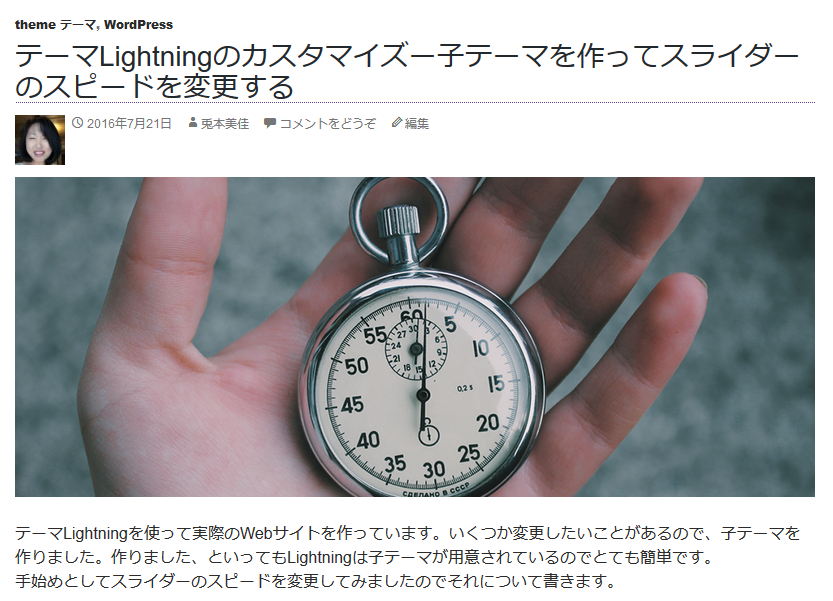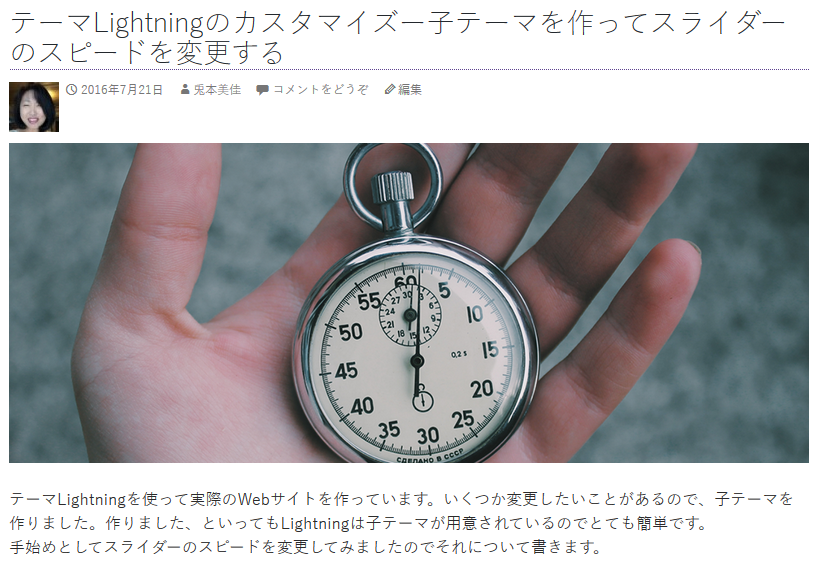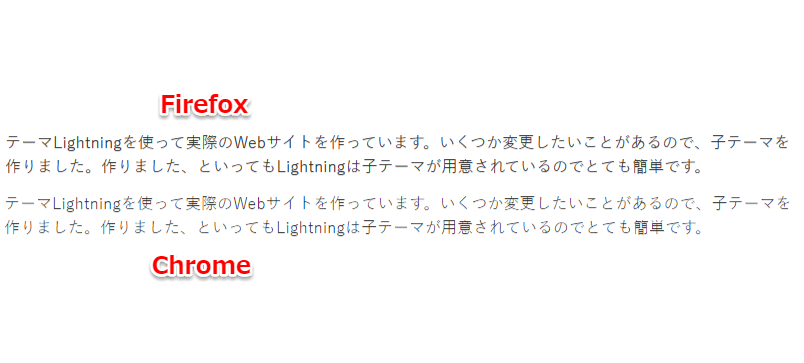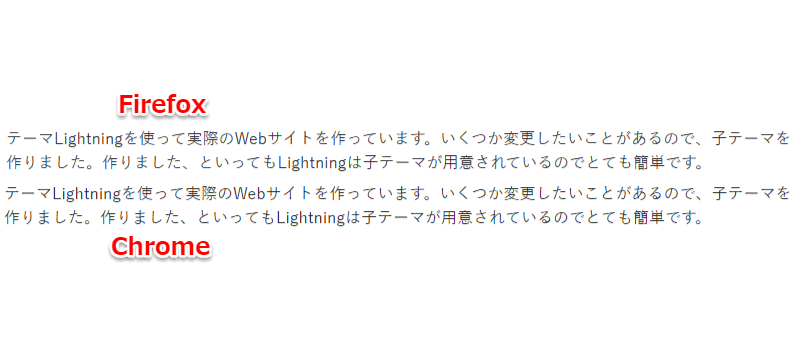
ブログのフォントをWindowsにもMacにもインストールされている游ゴシックに変えてみた
このblogは2年前の3月から書いていますが、当初に設定して以来font-familyを変更していませんでした。当時としてはこれがベスト!と思われる設定でした。
先日、WindowsにもMacにもインストールされている游ゴシックというフォントがあることに気づきましたのでそろそろfont-familyも変えてみようということで変更してみました。
font-familyで指定したフォントは各PCに入っているフォント
今(原稿を書いている)現在、このblogのfont-familyは
で指定したままとなっています。つまり、
です。font-familyで指定したフォントは、このblogをみてくれる人のPCなどが持っているフォントで表示されるためMacなら「ヒラギノ角ゴ ProN W3」で、Windowsなら「メイリオ」で表示されることになります。私がいつも使っているのはWindows10なのでメイリオでblogは表示されています。
WindowsでもMacでも同じフォントで表示したい場合は
で書いたようにWebフォントを使うことで実現できました。この方法ならWindowsでもMacでも同じフォントで表示できますが、設定が面倒だったりフォントが有料だったり、読み込みが遅くなったりします。
游ゴシック とは?
そこで游ゴシックの出番となります。游ゴシックはWindows8.1、MacではOS X Mavericksから標準搭載されました(その他に、游明朝もはいっています)。
それまではWindowsとMacに共通するフォントがなかったためにそれぞれ別のフォントで表示していたWebサイトも比較的新しいPCであれば同じように表示されるということになります。
游ゴシック、游明朝その他2書体をまとめて游書体という書体ということです。
このWikipediaをみると、「字游工房初の独自書体」ということだそうです。字游工房さんのWebサイトを見るとそれまでもかなり実績のあるフォント制作会社さんのようですが、はじめて作った独自書体がMacOSやWindowsに取り入れられるってすごい!なんだか映画になりそうな、気がしました。
font-familyに游ゴシックを追加してみてみる
font-familyに游ゴシックを追加してみます。子テーマのstyle.cssで
となっているfont-familyに
游ゴシックを追加しました。
今までは、
このように表示されていたものが、読み込み直すと
ちょっと線が細く、上品な感じ?のフォントになりました。
chromeだけ、色が薄くなってしまう問題を解決
先ほどのスクリーンショットはFirefoxでみたときのものなのですがChromeでみてみるとなんだかフォントが薄い?感じがします。
わずかですがChrome(とVivaldi)で見たときだけ薄いです(Edge,IEでは感じませんでした)。
これについて検索したところ、
Windowsで游ゴシックが汚いのは、どう考えてもWebデザイナーが悪い?
という記事を見つけました。どうもやっぱりChrome(とVivaldi)だけfont-weightが違う解釈になってしまうようです。
ということで、
文字の太さを指定する font-weight:500; を追加してみました。
再度読み込み直すと、
と、ChromeやVivaldiで見ても文字が薄すぎない状態になおりました。
問題発生!このblogで多用しているstrongが太文字にならない…
と、これで解決した…と思ったところ問題が発生しました。font-weightを指定する前は
このように太文字で表示されていた
Lightningの<strong>子テーマ</strong>は作成元である株式会社ベクトルさんが準備してくれています。
strong指定した文字「子テーマ」が、
なんということでしょう(;;)、太文字にならなくなってしまっています。うーん。
試しにfont-weight指定を外すと元のように太字になるので、どうもこの指定方法だとstrongで太文字にできなくなってしまうようです。。。
いろいろな情報でみなさんfont-weightで修正しているのでもしかするとtwentyfourteenの子テーマでなければ、大丈夫なのかもしれません。あるいはみなさんあまり strong を使われていなくて、この問題は気にならないのかもしれません。
しかし、太文字を多用している(^_^;このblogだと大きな問題になってしまいます。
フォントを游ゴシック Mediumに変更する
さて…と思って色々検索をしてみました。そしてこの記事を見つけました
Windowsの游ゴシックをfont-weightを使わずにMacに合わせる方法
ここに書いてあるようにWindowsをMacに合わせたいということではなかったのですが、試しにこの方法を取り入れてみました。
font-familyに “游ゴシック Medium”, “Yu Gothic Medium” を追加して、font-weightは削除しました。
これで読み直してみたところ、
文字の色も細すぎず(游ゴシック Mediumが指定してあるため)、strongが太字で(font-weightを指定してないため)表示されるようになりました。
まとめ:太字を多用しているWebサイトで游ゴシックを使うときは注意?
まだtwentyfourteenでしか試していないので、確かなことは言えないのですが游ゴシックをfont-familyで使うときは
・ChromeやVivaldiで文字のweightがなぜか低くなり 薄く見える
・かといって全体的にfont-weightを指定するとstrongが太文字にならなくなる(かも?)
ので、
・今時点で游ゴシックをfont-familyに追加するときは “游ゴシック Medium”, “Yu Gothic Medium”,”游ゴシック”, YuGothic,
を指定するのがよさそう
ということかなと思います。
* 2016/07/31 追記:やっぱり游ゴシックより元々の表示の方が RYUS blogっぽい気がして、元に戻しました(^_^;